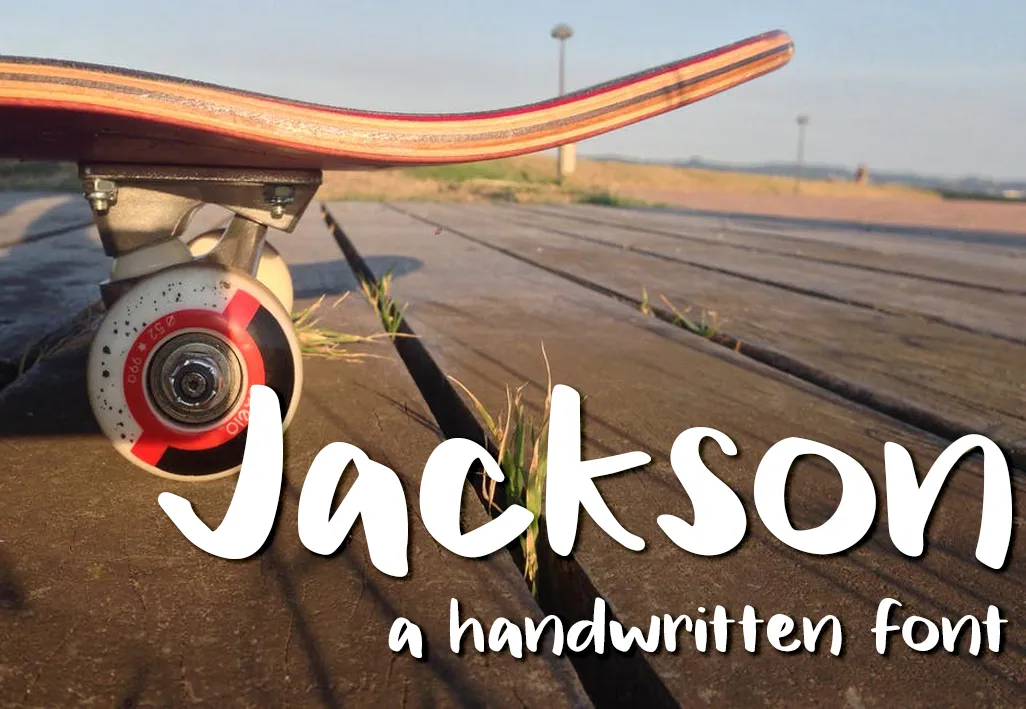
Jackson Font – Download Grátis
Bem-vindo ao download da nossa fonte ‘Jackson Font’. Nossa fonte é uma elegante caligrafia com traços fluidos e detalhes sutis que proporciona um toque personalizado a qualquer projeto de escrita ou design. Se você apreciou nosso trabalho, estamos realmente gratos por sua consideração em nos fazer uma doação simples, mas significativa. Um valor tão pequeno quanto $1 pode fazer uma enorme diferença ao permitir que nós, designers como o Groovyjournal, possamos dedicar mais tempo a nossa paixão pela criação de fontes únicas e detalhadas. Queremos expressar nossa gratidão sincera por fazer parte do seu processo criativo. Desde já, muito obrigado!